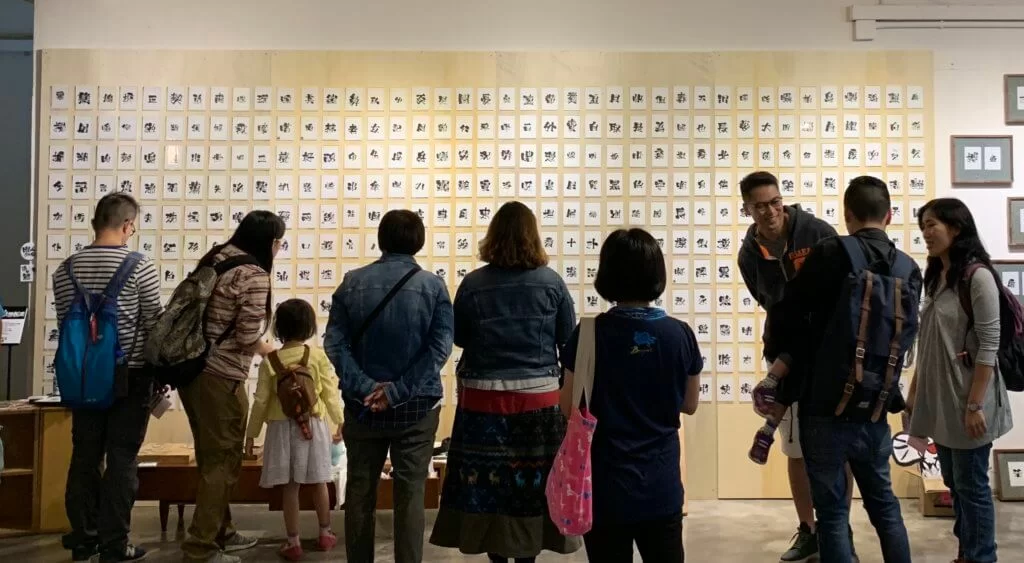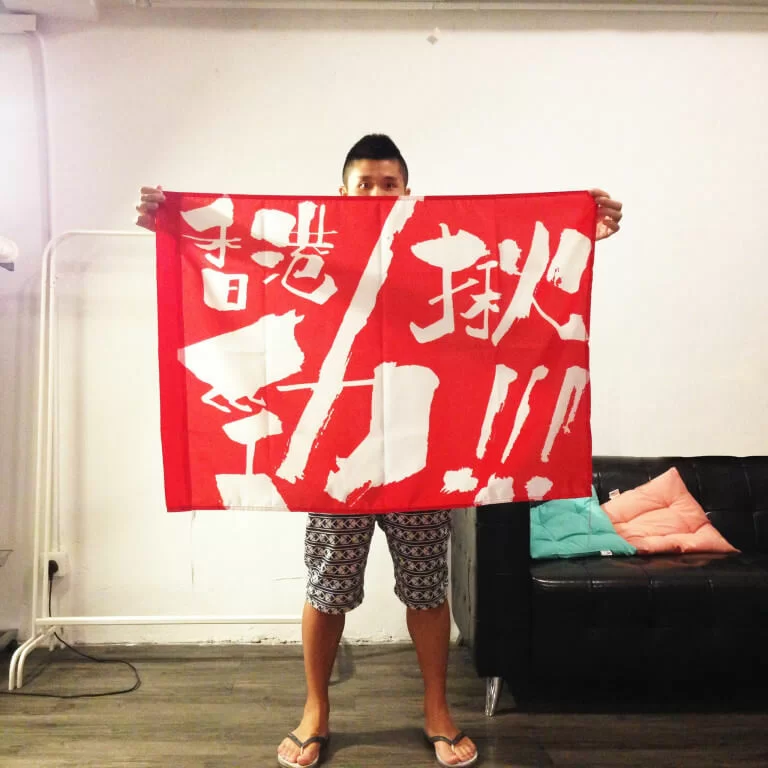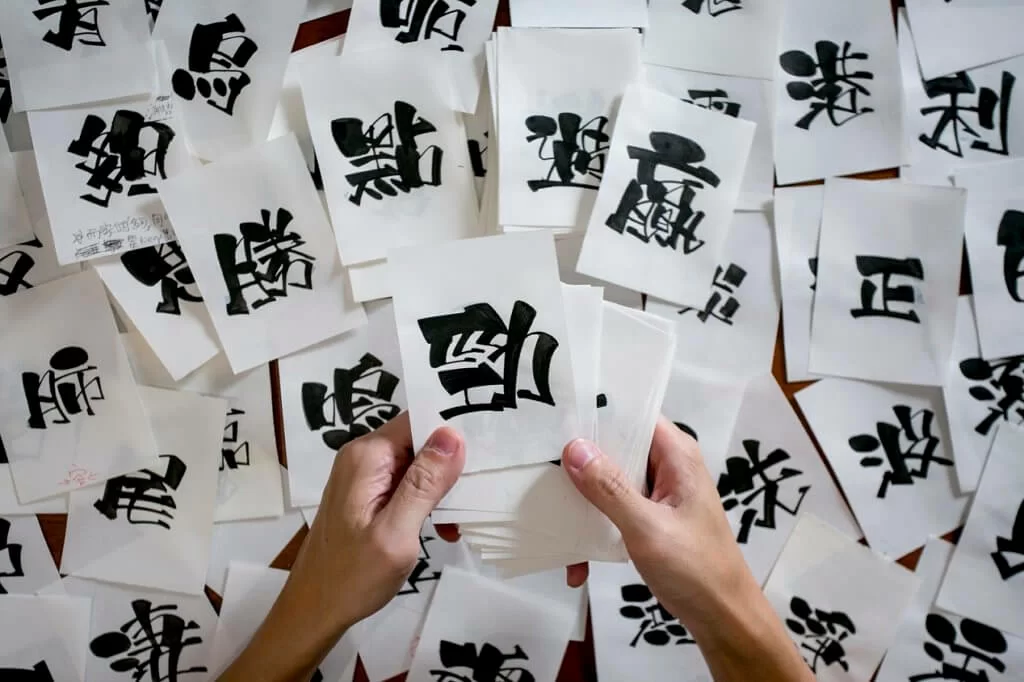
兩年前,「勁揪體」眾籌達標,創作人Kit Man多咗一堆課金支持的「老細」,開展日寫夜寫的生活。化歪歪斜斜毛筆字為好好睇睇的電腦字,可謂「粒粒皆辛苦」。揸緊信念瞓身七百三十天後,大嗱嗱六千粒字要出世了。Kit Man笑謂:「出咗個頭㗎啦﹗」為隆重地宣佈字體出籠,他搞了個「蚊型展覽」。現場有一個《原稿展區》,四百四十粒字內藏大量俗語,打橫打直打斜能組合出「塞竇窿」、「貪得意」、「餓狗搶屎」等等,考大家眼力及俗語造詣。另外亦有一個互動投影裝置《文字瀑布》,廣東話詞語從高處不斷掉下,閣下想抱住、撥開、推走皆可,玩法悉隨尊便。
他謂字體適合用於標題,形容製作字體是把製作標語的能力賦予他人。
Kit Man本業是多媒體設計,認為展覽不能沒有互動裝置。
四百多張原稿看出他不同階段的字體寫法略有不同。當中隱藏多個廣東話俗語,不妨與朋友鬥快找出。
有醜唔怕獻
這套字體被冠以「勁揪體」大名前,一直被他戲稱為「獻醜體」。「醜仲係照獻。基本字型都係醜㗎,但變成電腦字體後字與字之間的一體感強咗,外圍會比較方正,排列起來會順眼啲。」他自稱推出「勁揪體」是「連環獻醜」,皆因毛筆書法及字體設計都不是他的本業,卻認為能創作「勁揪體」,是福份,因為字體本來就是用以捍衛正體字及廣東話。「聽過有啲小朋友講講下廣東話會突然轉channel講普通話,有朋友的仔女用廣東話唔識表達抽像概念,只識用普通話。」普教中令我們的母語勢危,廣東話被邊緣化,他希望利用設計產品講述社會事件。「始終唔係睇到結果先至堅持,係堅持先知有無結果。」
「勁揪體」源於雨傘運動,曾被用以製作「我要真普選」橫額。這幾年,字體出現在多個活動的宣傳品上,他認為「勁揪體」最「勁揪」的一次出場,始終是港中足球大戰為香港隊打氣的「香港勁揪」旗幟。「嗰次比較多人留意,比起用於政治口號傳播得更廣。字在旗上視覺衝擊好大。」球迷揮舞「香港勁揪」紅旗撐自己人,零舍熱血沸騰。
蝕入肉捱下去
得到多位「老細」支持,他認為字體盛載社會責任,他接廣告或與機構合作都會三思。「始終要對支持者負責,都推過job。」有人認為他籌六十五萬製作一套字體相當豐足,他笑指「勁揪體」是蝕本貨。「當初計漏好多嘢,要搵律師做文件、開發拼合字體軟件、一個助理唔夠、工作室加租等等。又唔可以接好花時間嘅job,怕唔可以如期完成。」他說去年完全沒有額外工作,只靠前年的工作酬金過活。「戶口數字插水,想衝又唔可以衝,始終未完成唔可以計劃未來其他嘢,真係只可以活在當下,面對現實。」「勁揪體」接近完成階段,他突然獲得多個工作機會。「好似食屎食到一個點,突然跌一啖砂糖落來咁。」否極泰來這句話,嗒落有智慧。